Строчная «ю» в рукописном шрифте: как связать стойку и овал
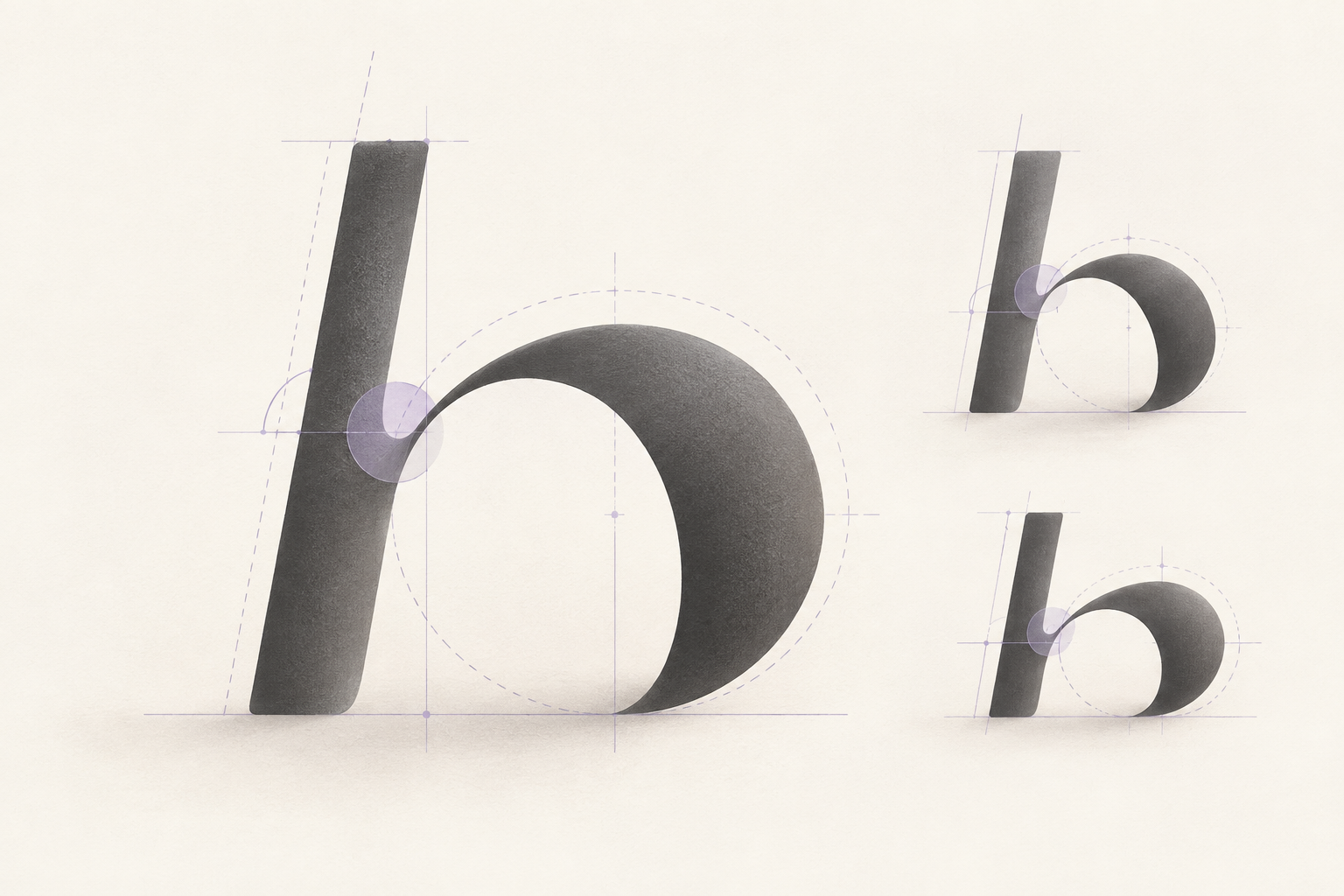
Строчная «ю» строится из вертикальной стойки и округлой части, но простого соединения двух готовых элементов недостаточно: буква может выглядеть тяжёлой слева, распадаться на «и» с овалом или казаться тесной. Чтобы этого избежать, сначала определите пропорции стойки и овала относительно строчных «н», «о» и «а», затем выберите место перехода и проверьте силуэт в коротких словах. В этом руководстве — последовательность эскизов и критерии, по которым можно оценить результат без сложных измерений.
Почему «ю» требует отдельного решения
В букве одновременно действуют два разных зрительных центра. Стойка задаёт левую границу и воспринимается как самостоятельный вертикальный штрих, а овал несёт основную округлую массу. Если обе части рисовать независимо, стык становится случайным: овал либо врезается в стойку слишком глубоко, либо отходит от неё и оставляет щель. Читатель замечает не детали построения, а неустойчивый общий контур — буква кажется шире, тяжелее или менее связной, чем соседние знаки.
Сначала решите, каким должен быть характер алфавита: спокойным и компактным, свободным и покатым или более геометричным. Эта установка влияет на наклон стойки, степень вытянутости овала, округлость перехода и длину входного штриха. Не нужно делать «ю» миниатюрной иллюстрацией всего почерка: достаточно согласовать с уже выбранной системой наклон, толщину и пластику. Самые заметные решения должны повторять правила других букв, а локальные особенности — поддерживать узнаваемость «ю».
Соберите ориентиры до первого чистового контура
Для пропорций полезно поставить рядом несколько уже нарисованных строчных: «н» показывает рабочую высоту и характер стойки, «о» — форму и ширину круглой части, «а» помогает сравнить плотность закрытого овала, а «и» — наклон и пластику вертикального элемента. Эти буквы не являются жёсткими лекалами. Они дают относительные ориентиры: насколько стойка «ю» близка к обычной стойке, не становится ли овал шире круглых форм алфавита и сохраняется ли общая высота.
Нарисуйте по три быстрых варианта, меняя только один параметр за раз. В первом измените ширину овала, во втором — отступ его левой точки от стойки, в третьем — высоту и наклон стойки. Подпишите на бумаге, что именно менялось, чтобы не полагаться на память. Если одновременно менять все характеристики, сравнение ничего не объяснит. Эскизы должны быть достаточно крупными, чтобы видеть переход, но достаточно простыми, чтобы легко исправлять силуэт.
Выберите ширину овала и нагрузку стойки
Начните с овала, близкого к принятой в алфавите строчной «о». Затем поставьте рядом «ю» и сравните не только внешнюю ширину, но и внутренний просвет. Одинаковый внешний размер не гарантирует одинакового ощущения: у «ю» стойка занимает часть общей ширины, поэтому округлая часть может визуально стать теснее. Иногда её нужно немного расширить или сделать мягче по бокам. Такая поправка не должна превращать «ю» в самую широкую букву строки без причины.
Стойка тоже не обязана быть копией штриха из «н». В соединённой форме она может получить чуть иной вход, наклон или верхнее окончание. Но её толщина должна принадлежать тому же диапазону, что и другие вертикали. Если левый штрих кажется темнее, попробуйте сначала уменьшить локальное утолщение в стыке, а не делать всю стойку тоньше: иначе буква потеряет опору. Если стойка выглядит слишком массивной, проверьте её ширину и наклон в слове, а не только изолированно.
Найдите место соединения
Надёжный стык — это короткий и понятный переход от вертикального движения к округлому. Поставьте соединение так, чтобы левая часть овала не исчезала за стойкой и чтобы внутренняя белая форма не превращалась в узкий клин. В рукописном рисунке переход может быть прямым, скруглённым или слегка диагональным; выбирайте форму, которая соответствует привычным соединениям в других знаках. Если в алфавите штрихи соединяются плавно, резкий угол на «ю» будет выглядеть чужим.
Проверьте, куда направлена линия в месте перехода. У овала есть верхняя и нижняя касательные: если стойка встречается с ним под неожиданным углом, получается тёмный узел или локальный излом. Попробуйте слегка сдвигать точку входа вверх и вниз, сохраняя общий размер. Затем сравните, где соединение проще продолжить рукой и где белое пространство остаётся открытым. Физическая удобность движения важна для рукописного характера, даже когда конечный контур уже будет цифровым.
Не маскируйте сомнительный стык дополнительной петлёй или декоративным росчерком. Сначала упростите конструкцию до двух основных частей и добейтесь ясного перехода. Только после этого решайте, нужен ли входной штрих, выход или небольшая асимметрия. В сложной форме украшение часто становится попыткой спрятать неудачное соединение, а не осознанной чертой стиля.
Согласуйте высоту, наклон и оптический баланс
Высоту овала сверяйте с высотой округлых строчных, а верх стойки — с верхними точками соседних букв. Если у алфавита заметный общий наклон, стойка «ю» должна его поддерживать, но не обязана повторять угол механически: соединение с овалом может оптически выпрямлять левую часть. Посмотрите на букву в строке без направляющих. Если вершина кажется выше остальных, опустите её чуть-чуть; если низ «проваливается», скорректируйте основание. Речь о визуальном равновесии, а не об одинаковых координатах всех точек.
Сравнивайте массу по обе стороны стойки. Поскольку овал находится справа, буква может казаться перевешенной даже при симметричном контуре круглой части. Часто помогает немного укрепить левую стойку, сместить овал ближе или изменить его ширину. Исправляйте только то, что видно при нормальном размере слова: чрезмерные микропоправки в увеличенном эскизе могут исчезнуть при наборе и добавить лишнюю сложность.
Проверьте «ю» в окружении
Изолированная буква показывает конструкцию, а слово — её реальное поведение. Наберите или напишите несколько коротких слов с «ю» в разных позициях: в начале, середине и конце. Например, сравните «юла», «люблю», «уют», «июнь». Это не контрольный список правильных сочетаний, а способ увидеть разные соседства: округлые знаки, вертикали, диагонали и пробелы. Отдельно посмотрите, не сталкивается ли овал с соседней буквой и не возникает ли случайная широкая пауза.
Затем прочитайте строку на привычной для проекта длине. В коротком слове форма может выглядеть выразительно, но при повторении несколько раз подряд проявится чрезмерная ширина или тяжёлый левый край. Наберите серию «ююю» и сочетания «ою», «ую», «ню»: они быстро показывают, одинаково ли работают округлая часть и стойка. После этого уменьшите масштаб просмотра. Если характер сохраняется, конструкция устойчивее, чем если она читается только в крупном эскизе.
- Изолируйте эскиз: проверьте внешнюю форму, высоту и внутренний просвет.
- Сравните «ю» с «н» и «о», не копируя их механически.
- Проверьте три варианта стыка, меняя только его положение или угол.
- Поставьте букву в короткие слова и повторяющиеся сочетания.
- Уменьшите размер и оцените, не слиплись ли стойка и овал.
- Зафиксируйте выбранную версию и проверьте её после паузы свежим взглядом.
Частые ошибки и способы исправления
Первая ошибка — рисовать «ю» как готовое «н», к которому приставили уменьшенную «о». Так появляется жёсткая конструкция с разным ритмом: стойка выглядит из одного почерка, овал — из другого. Исправление — искать единый жест: построить овал в той же пластике, выбрать согласованный наклон и сделать переход продолжением движения. Вторая ошибка — увеличивать овал до тех пор, пока он не станет главным элементом. Сравнивайте ширину всей буквы с соседями, а не только округлую часть со строчной «о».
Третья ошибка — оставлять слишком узкий внутренний просвет в месте соединения. На большом рисунке он ещё заметен, но в строке быстро темнеет. Откройте просвет небольшим сдвигом стойки или овала; не раздвигайте элементы так далеко, чтобы форма распалась. Четвёртая ошибка — выравнивать все точки по линейке и забывать о зрительном балансе. Контур может быть формально ровным, но казаться кривым из-за ширины овала и направления входа. Финальное решение принимайте по пробной строке.
Пятая ошибка — исправлять знак только в одном размере. Если нужна версия для рукописной имитации в крупном заголовке, отдельные детали можно адаптировать, но сначала добейтесь работающей базовой формы. Для цифрового шрифта одна и та же буква будет появляться в разных кеглях и сочетаниях; проверяйте её там, где её действительно будут читать. Если вы создаёте шрифт из заполненного шаблона, полезно сравнить исходный рисунок с извлечённым контуром: автоматическая обработка может сгладить острый переход или закрыть тонкий просвет.
Как перенести эскиз в цифровой алфавит
Когда пропорции выбраны, перенесите букву в рабочую сетку и сохраните промежуточную версию. Следите за двумя контурами: внешним силуэтом и внутренней формой овала. Не добавляйте много узлов ради точности — несколько осмысленных опор обычно проще редактировать, чем цепочку мелких точек. Сначала повторите уверенный жест внешней части, затем проверьте просвет и стык. Сравните цифровую форму с соседними знаками на одной строке, а не в отдельных окнах.
Если вы создаёте алфавит на бумажном шаблоне, рисуйте овал и стойку достаточно отчётливо, не заштриховывая место соединения. На фото или при извлечении важно сохранить именно тот просвет, который вы спроектировали: тень, слабый контраст или слишком тонкая линия могут визуально изменить форму. После обработки проверьте границы знака и масштабируйте его рядом с остальными буквами. Для создания собственного набора можно использовать Fontgenerator: загруженный рисунок станет отправной точкой, которую стоит осмотреть и при необходимости доработать.
Нужно ли делать овал «ю» точно таким же, как строчную «о»?
Нет. «О» — полезный ориентир для ширины и пластики, но стойка меняет общий баланс и занимает часть пространства. Овал может потребовать небольшой коррекции, чтобы буква не казалась тесной или чрезмерно широкой в строке.
Должна ли стойка «ю» быть вертикальной?
Не обязательно. Её наклон зависит от общего почерка, но он должен поддерживать ритм алфавита. Сверяйте стойку с вертикальными штрихами соседних букв и оценивайте её в слове: оптически она может восприниматься иначе, чем в изоляции.
Как понять, что место соединения слишком тёмное?
Если при уменьшении буквы стык превращается в плотный узел, а внутренний просвет сужается сильнее, чем в других знаках, соединение стоит упростить. Попробуйте изменить угол или немного развести части, сохраняя цельность внешнего контура.
Можно ли оставить между стойкой и овалом маленький разрыв?
Можно, если разрыв является правилом всего алфавита и не заставляет «ю» выглядеть как два независимых знака. Проверьте такой вариант в быстрых сочетаниях и обычном размере текста. В связном рукописном стиле открытая щель часто воспринимается как случайный дефект.
С чего начать, если «ю» выглядит слишком тяжёлой?
Сравните толщину стойки со штрихами «н» и «и», затем посмотрите на место соединения и ширину овала. Часто достаточно убрать локальное утолщение у стыка или немного изменить наклон. Не уменьшайте одновременно все элементы: иначе будет трудно понять, что помогло.
Как проверить «ю» после сканирования шаблона?
Сравните обработанный знак с исходным рисунком: остался ли внутренний просвет, не сгладился ли переход и не изменилась ли толщина стойки. Затем поставьте его в несколько слов и уменьшите изображение до ожидаемого размера использования.
Нужно ли делать «ю» одинаковой ширины во всех стилях шрифта?
Нет. В компактном начертании овал и стойка могут располагаться плотнее, а в свободном рукописном стиле части могут раскрыться. При этом общая высота и характер перехода должны оставаться узнаваемыми внутри конкретного алфавита.
Короткий вывод